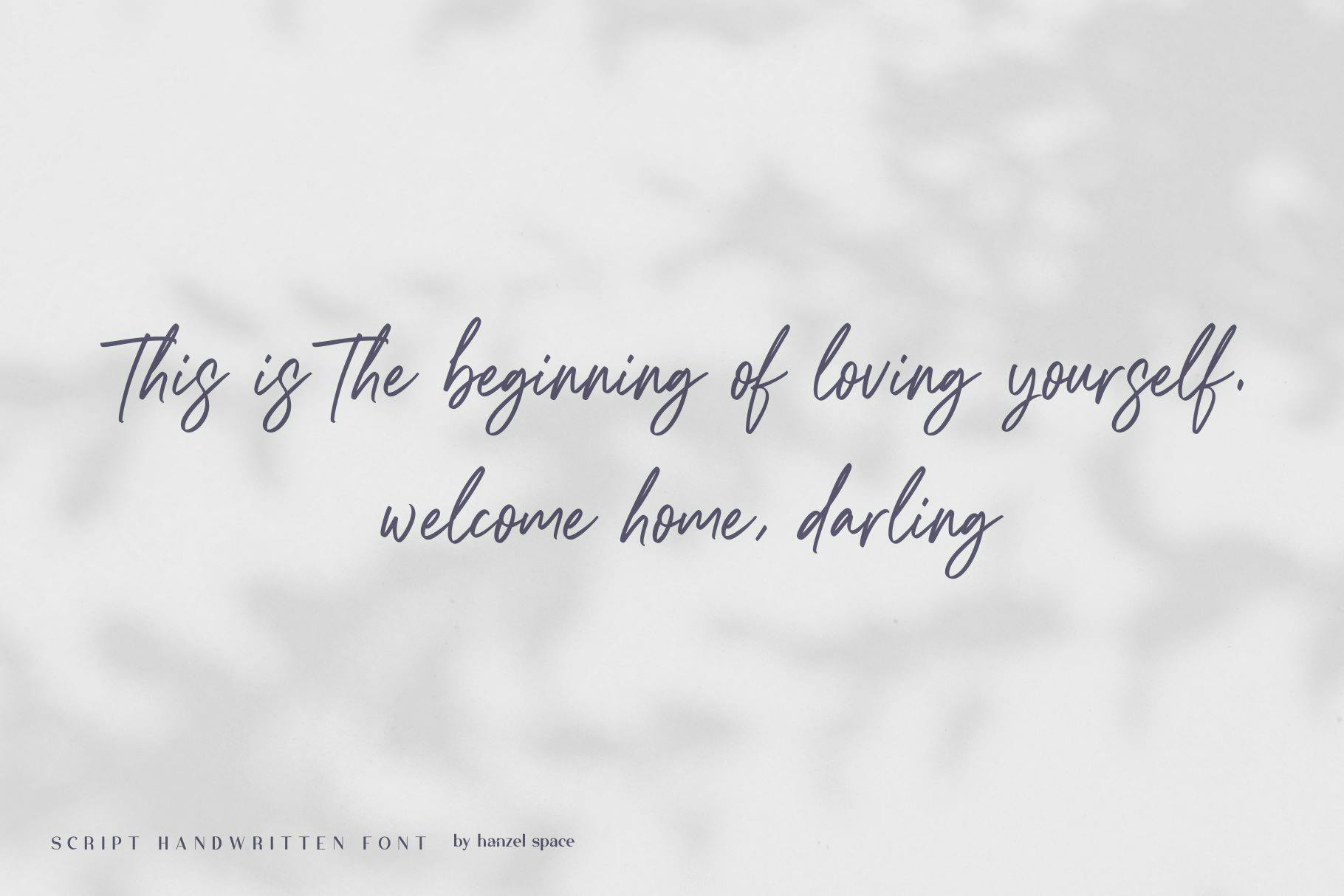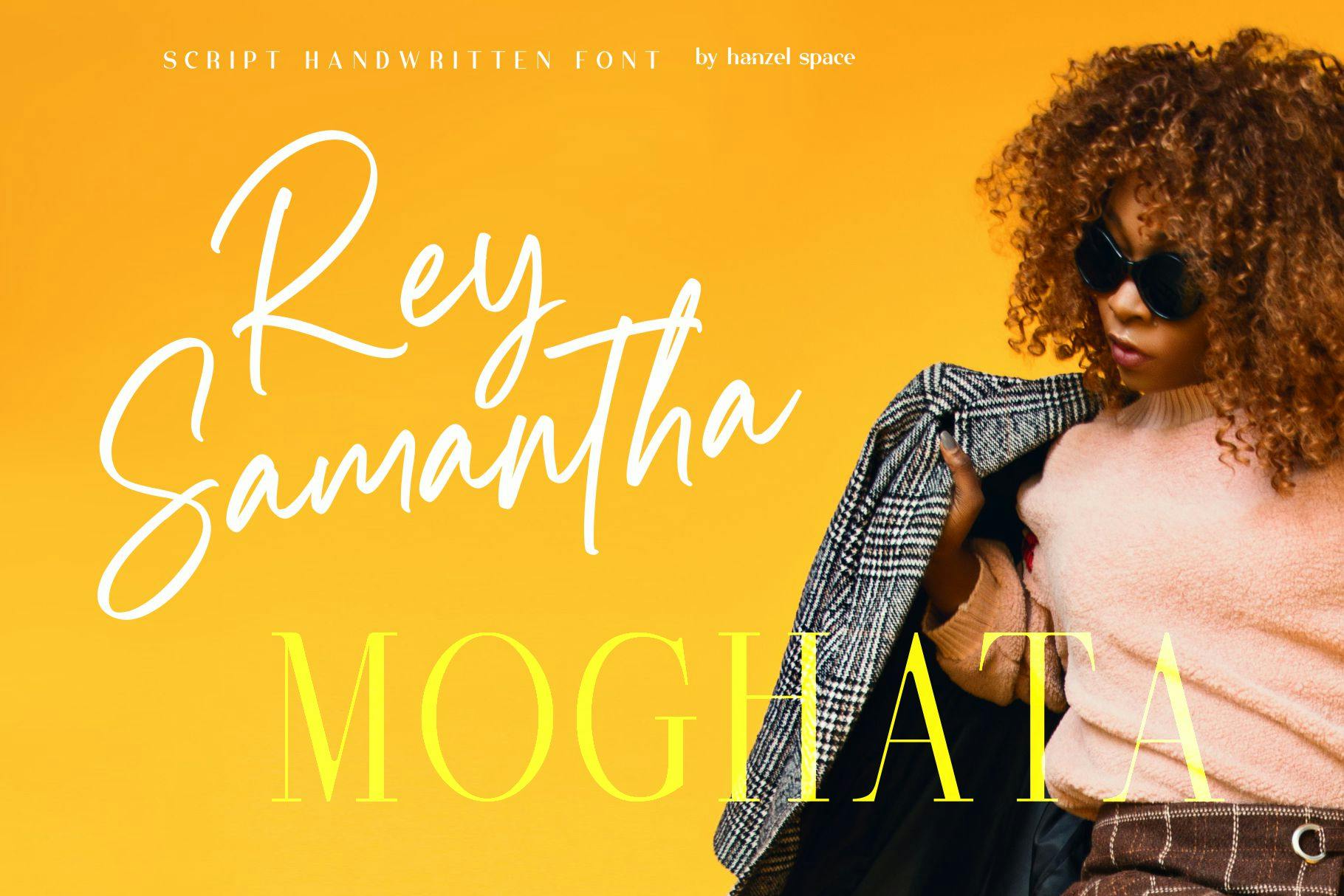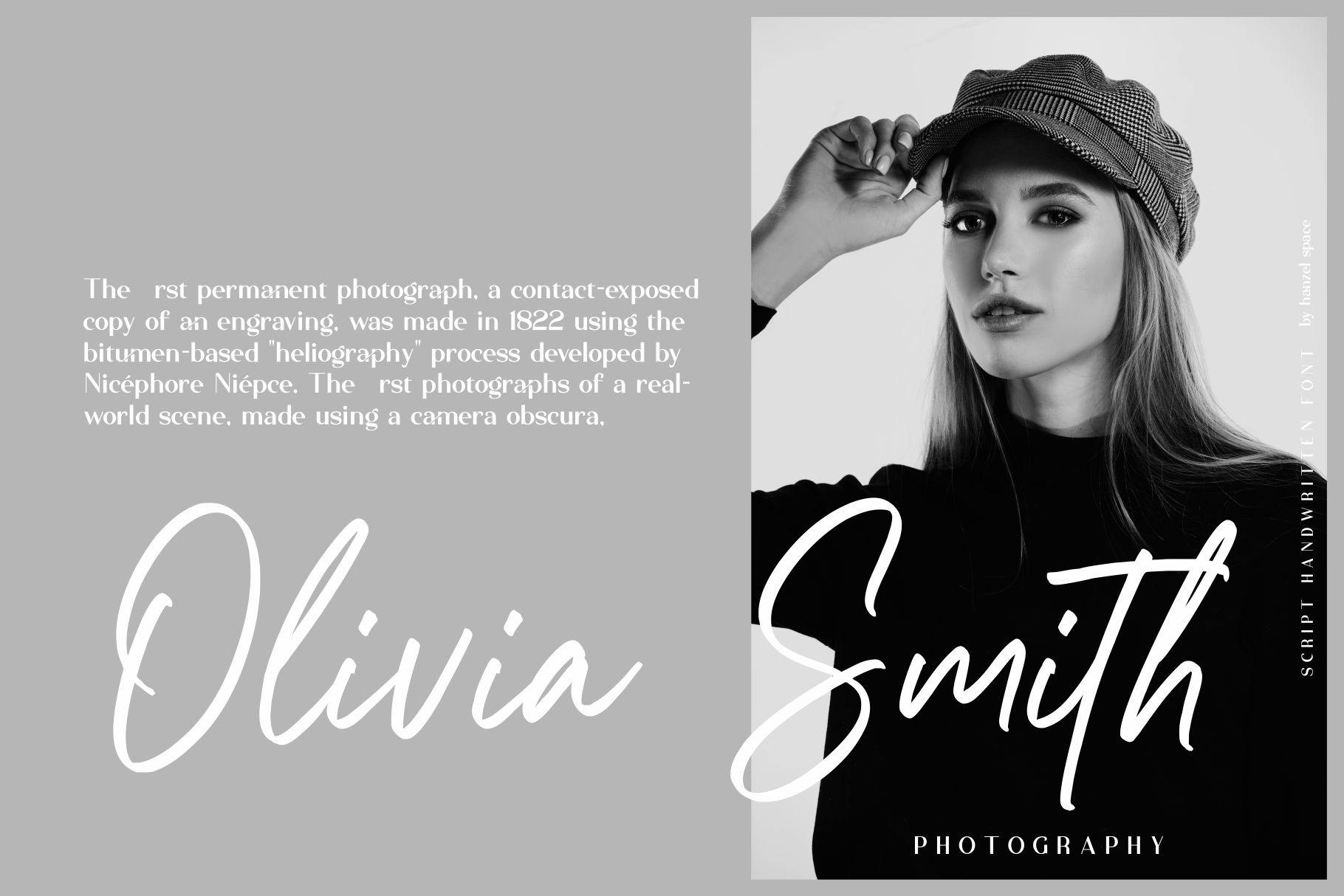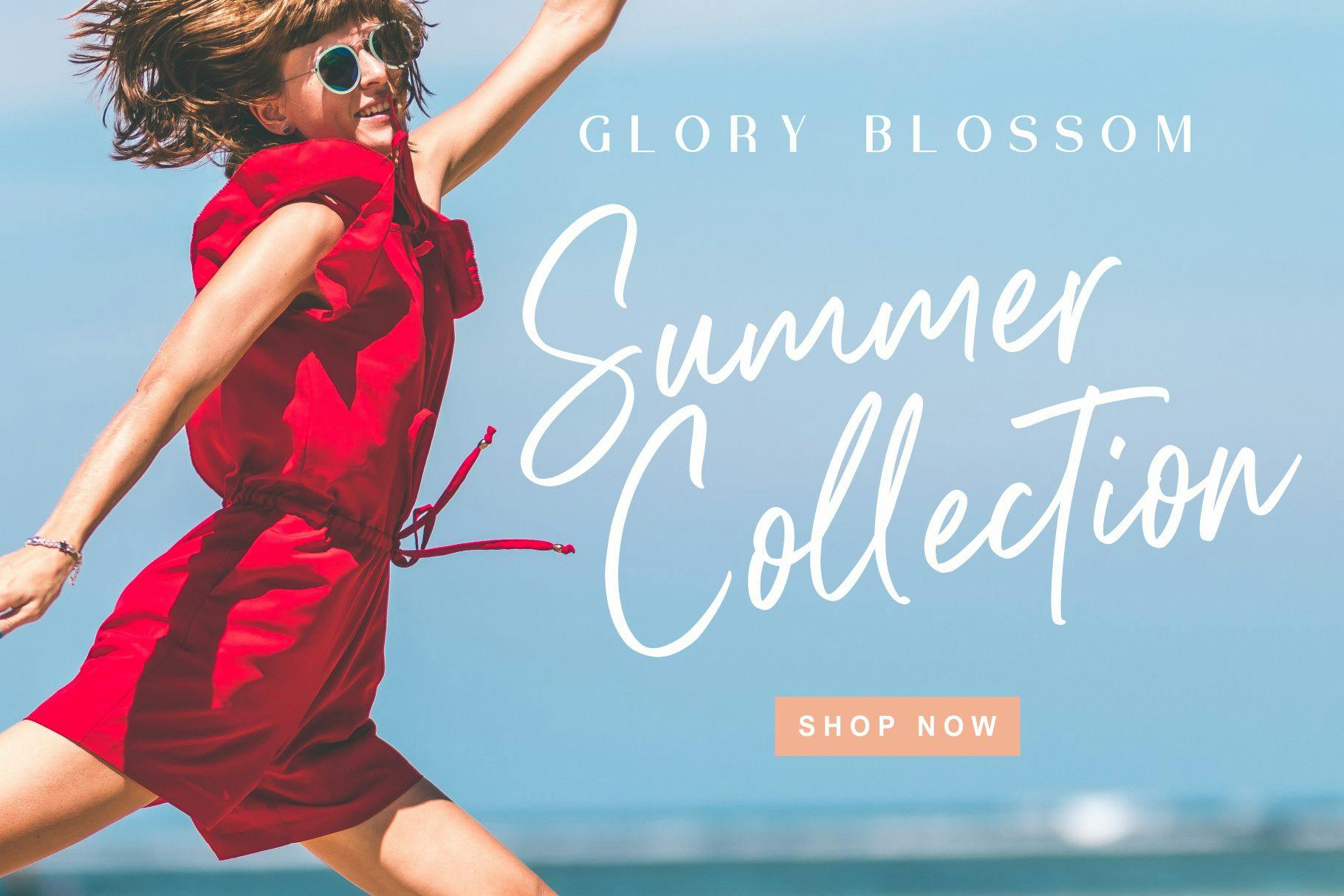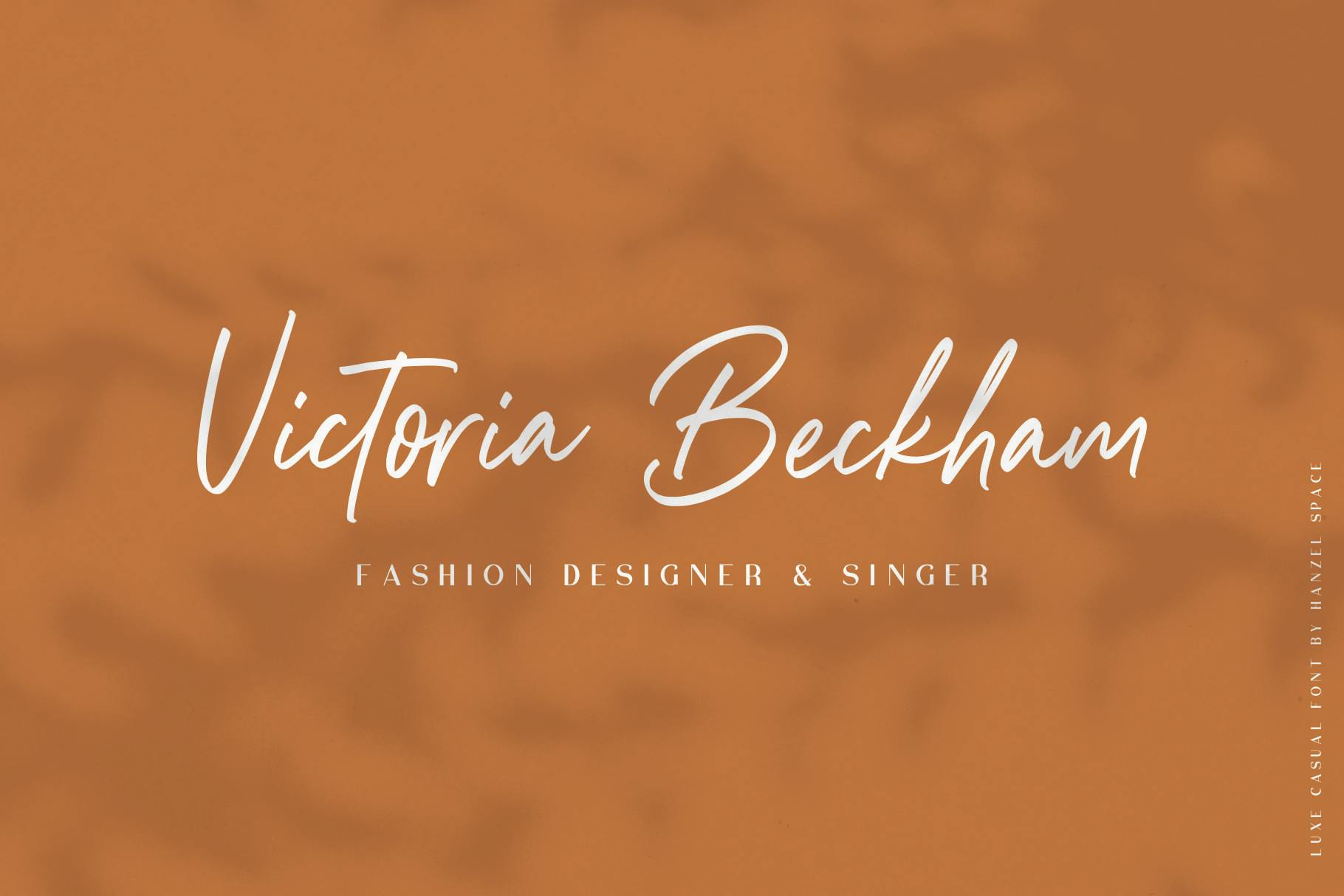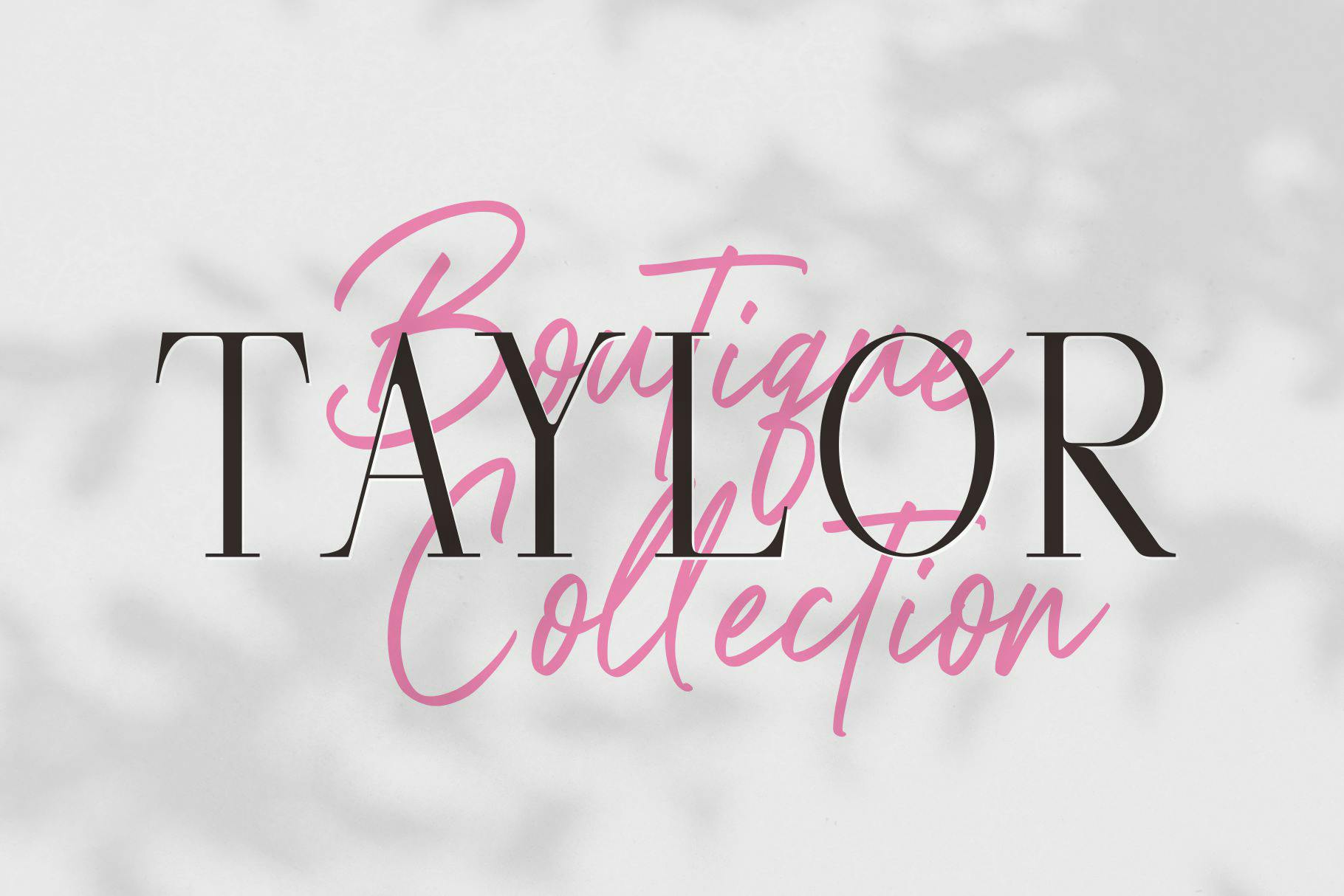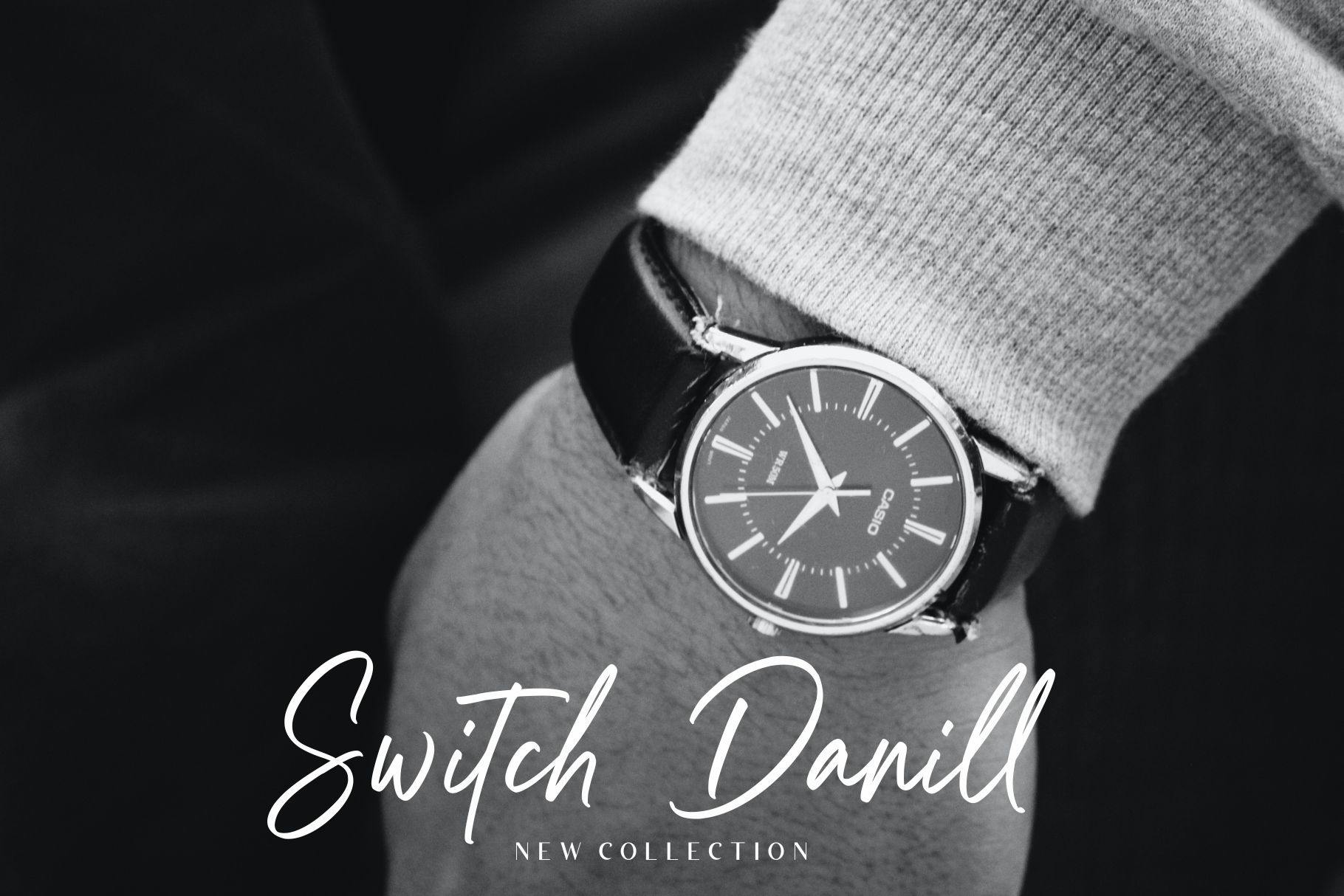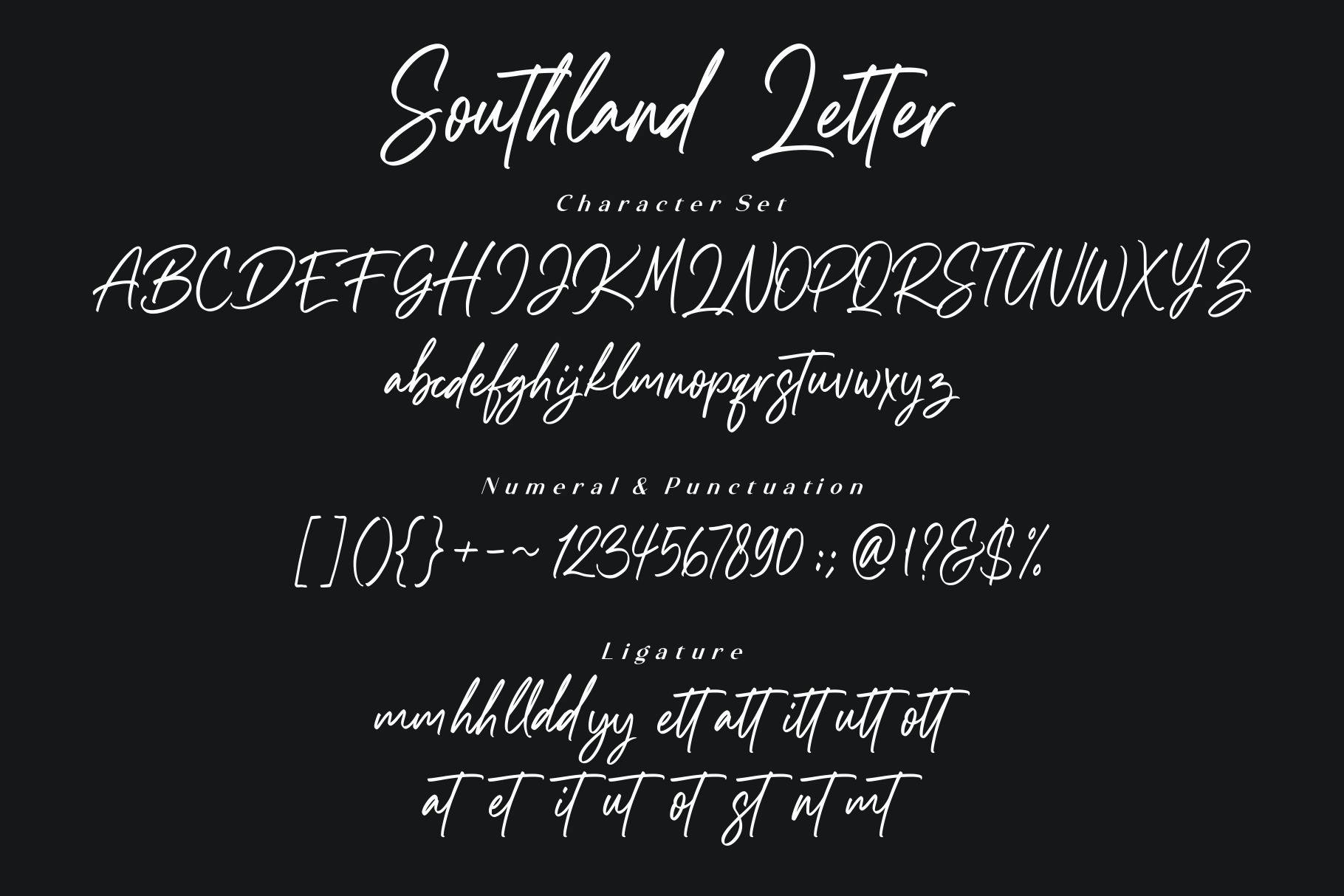
فونت دستنویس Southland با لهجههای معاصر و پیچیده، گزینهای ایدهآل برای برندینگ، دعوتنامههای عروسی، تگلاینها، کارتها و حتی برچسب و لوگو میباشد.
این فونت شامل مجموعه کاملی از حروف بزرگ و کوچک، اعداد، دامنه وسیعی از نشانهگذاری و لیگاتورها است. زیبایی خطخطی را به نمایش میگذارد. شما چه چیزی دریافت میکنید، عزیزم؟